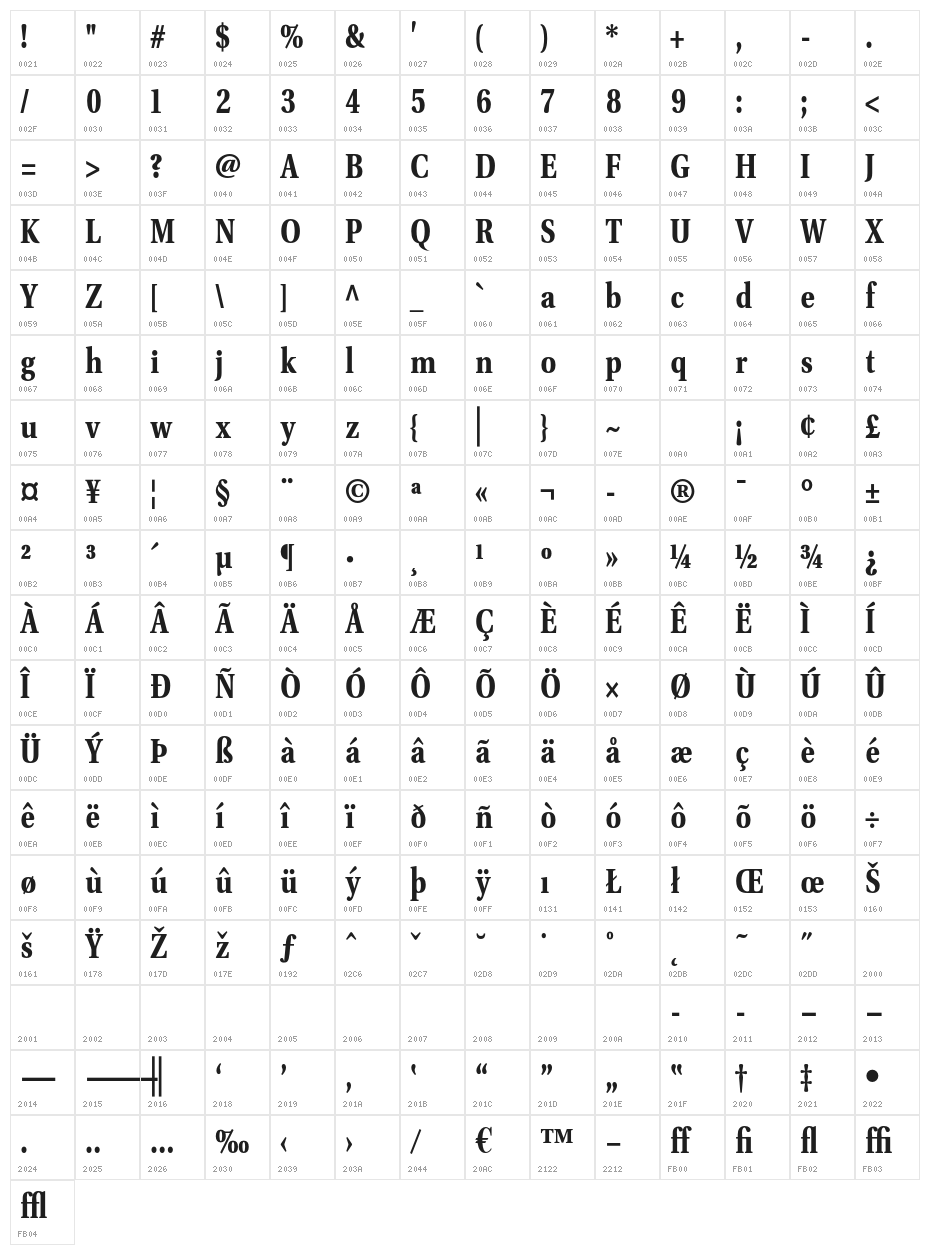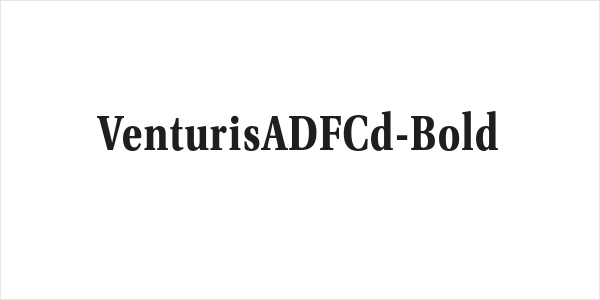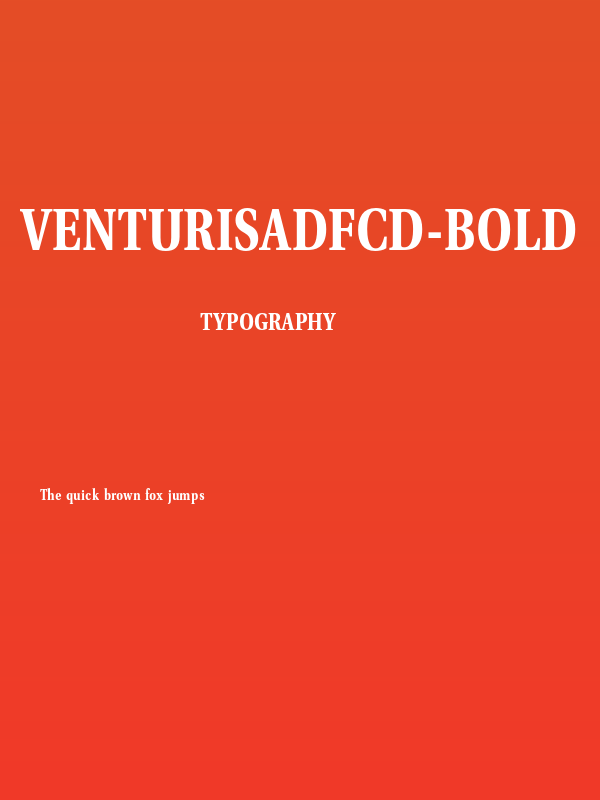
VenturisADFCd-Bold Font
Fonts by Arkandis Digital Foundry
| Gesamtstil | Classic |
| Vorgeschlagene Projekte | Ideal for editorial design, book covers, branding, and advertising where a strong, authoritative presence is needed. |